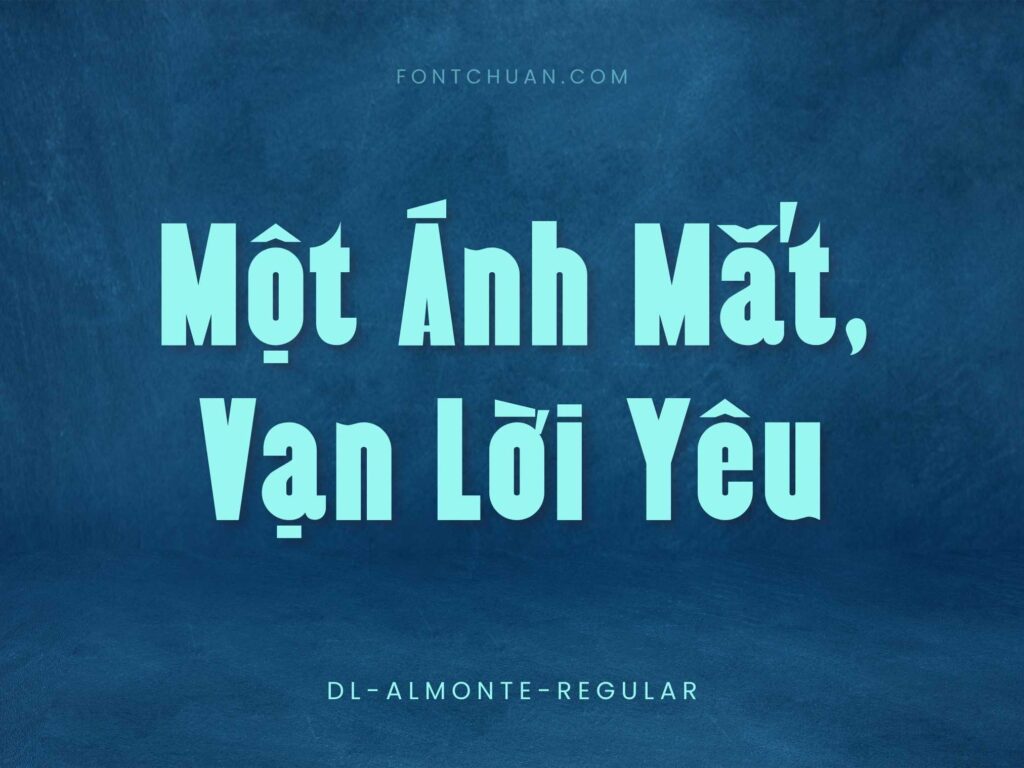
Font DL Almonte Việt Hóa
Tác giả Font: Raymond Larabie
Almonte là một kiểu chữ độc đáo, mang phong cách trang trại với thiết kế gỗ mộc mạc. Được tạo ra bởi nhà thiết kế Ray Larabie, font này mang đến cảm giác cổ điển và ấm áp, phù hợp cho các dự án thiết kế liên quan đến chủ đề nông thôn, steampunk hoặc các chủ đề lịch sử sáng tạo. Đặc biệt, Almonte đã được Việt hóa bởi Tduy, hỗ trợ tiếng Việt cùng nhiều ngôn ngữ khác, đáp ứng nhu cầu đa dạng của người dùng. Font này được sưu tầm và đăng tải bởi thành viên của Font Chuẩn, giúp cộng đồng thiết kế dễ dàng tiếp cận và sử dụng trong các dự án của mình.
Về đặc điểm thiết kế, Almonte sở hữu các ký tự dày dặn, với các đường nét gợi nhớ đến kết cấu gỗ, tạo nên sự mạnh mẽ và thu hút. Font này phù hợp cho các thiết kế như tiêu đề, poster, logo, bao bì sản phẩm và các ấn phẩm truyền thông cần sự nổi bật và cá tính. Ngoài ra, Almonte còn thích hợp cho các ngành nghề như quảng cáo, ẩm thực, thiệp cưới và spa, cùng các sự kiện đặc biệt như lễ hội, sinh nhật, Halloween và Trung thu.